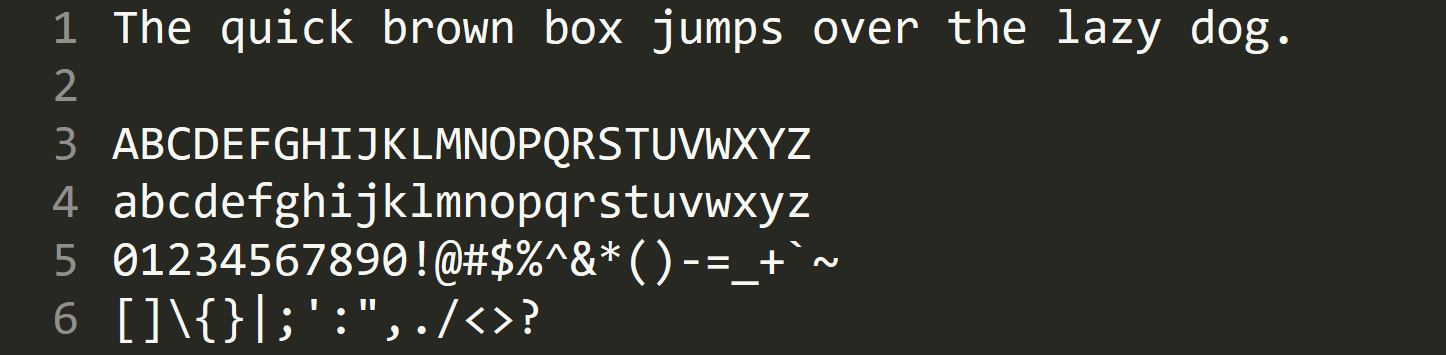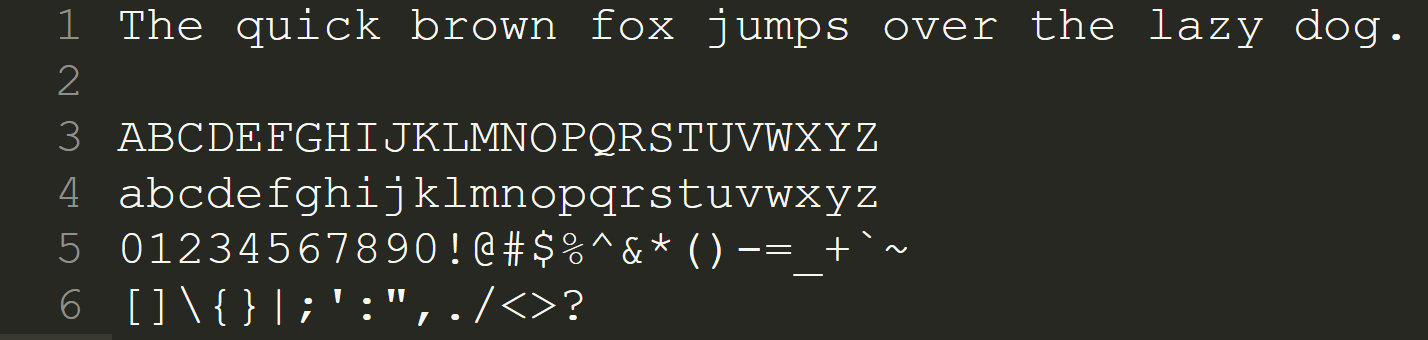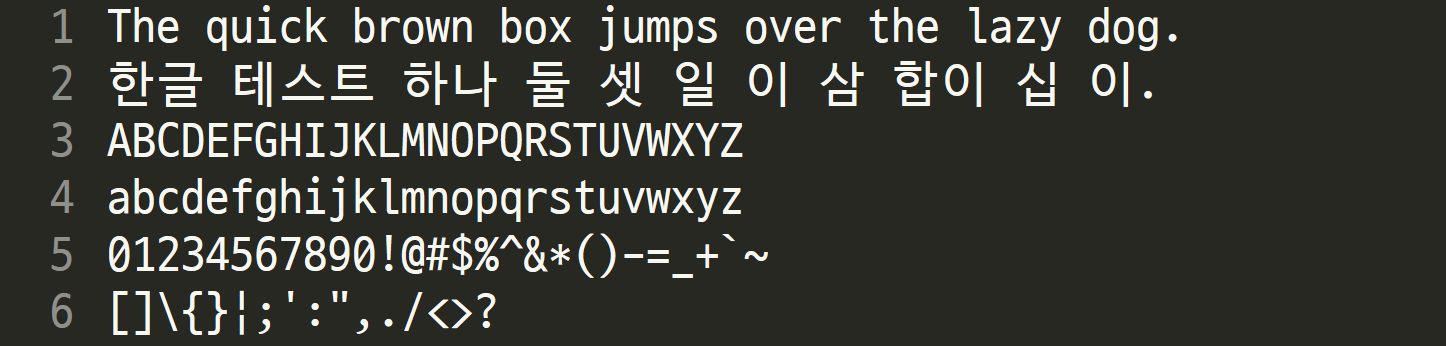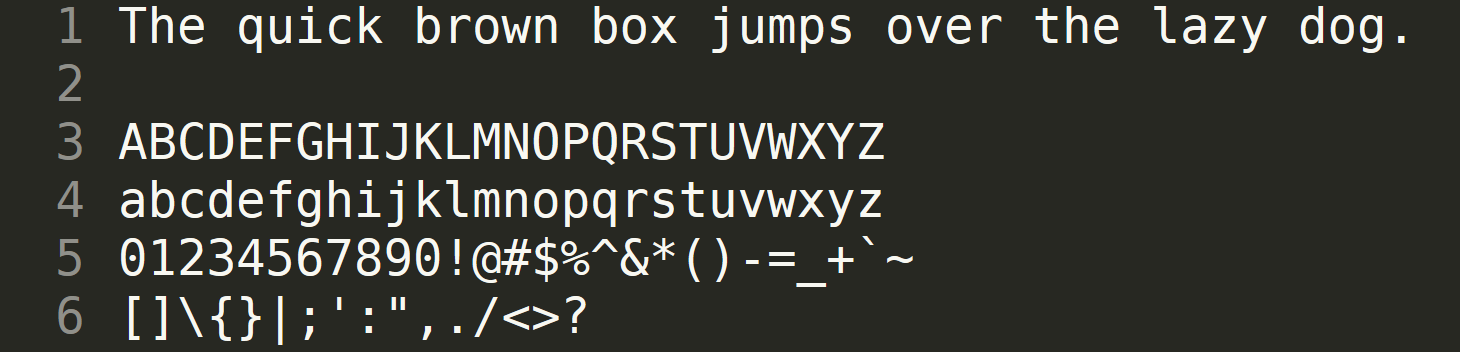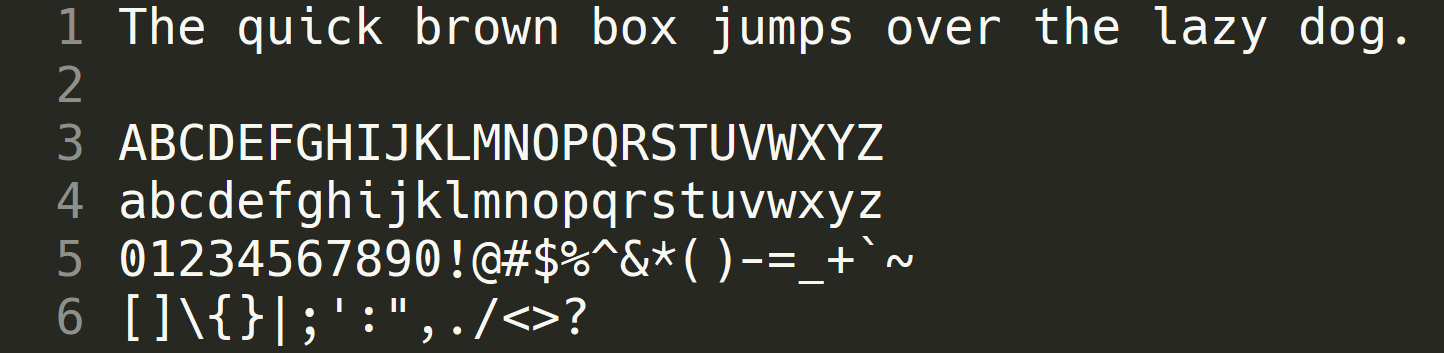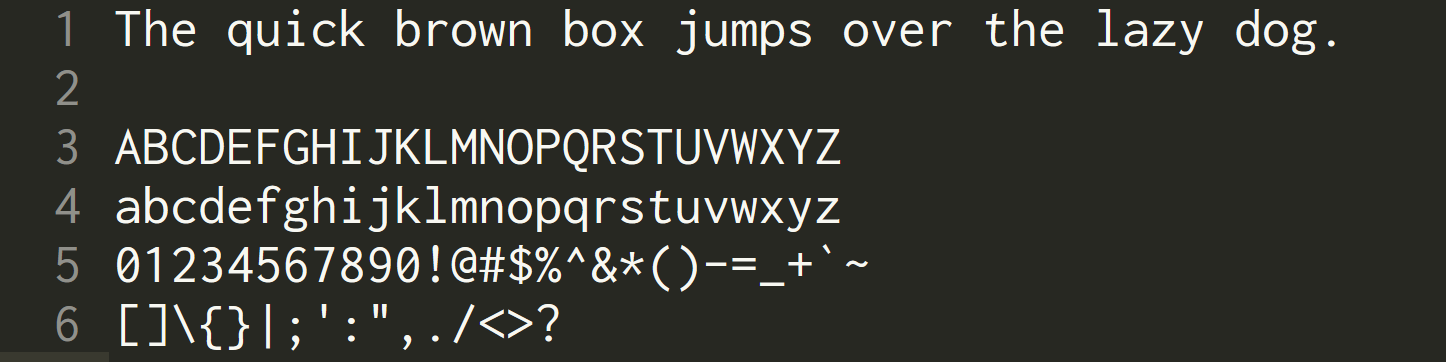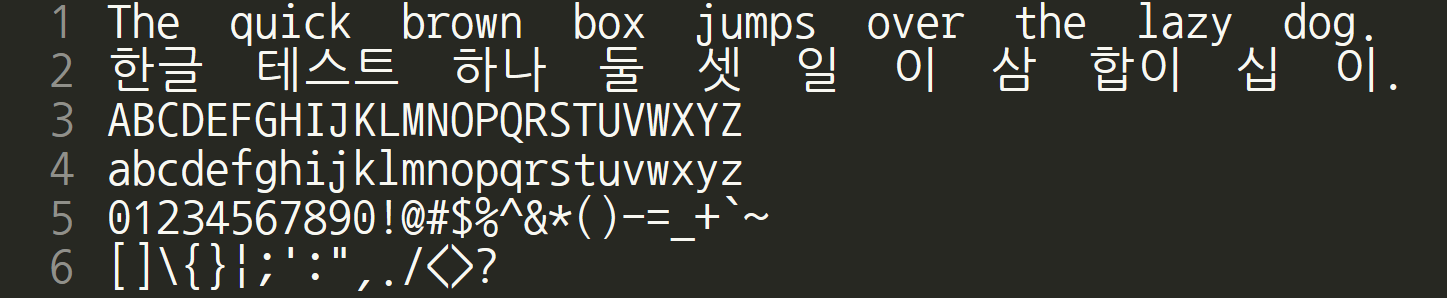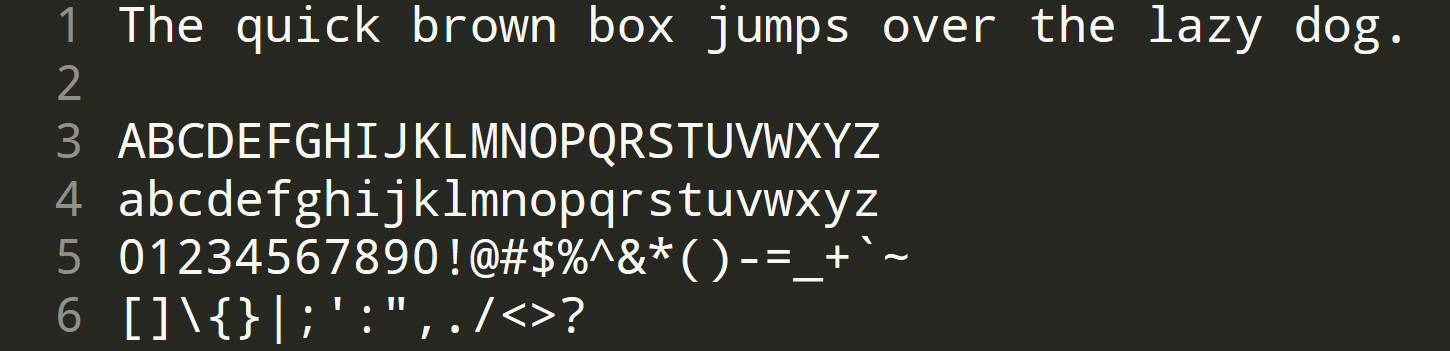
이공계 대학생/대학원생을 위한 컴퓨팅 강좌 8: 코딩용 고정폭 폰트(fixed-width font) 선택하기
고정폭 폰트의 필요성
코딩을 할 때는 기본적으로 글자의 가로 폭이 일정한 고정폭 폰트(fixed-width font)를 씁니다. 그 이유는 아무래도 터미널(terminal)에서 고정폭 폰트로 코딩을 하던 관습의 영향이 크겠습니다만 고정폭 폰트가 들여쓰기(indentation)와 같은 특성을 가진 소스 코드의 가독성을 높여준다는 이유도 있겠습니다.
그리고 코딩용 폰트는 1, i, l, | 이나 o, O, 0, @ 등과 같이 비슷하게 생긴 영문자, 숫자, 특수기호의 구분을 명확히 해야 하는 특성이 있습니다. 이것은 코딩을 할 때 한 글자만 틀려도 결과가 다르게 나오는 코딩의 특성 때문입니다. 실제 제 경우 학부시절에 for (j = i + 1; j < n; ++j)for (j = 1 + 1; j < n; ++j)로 잘못 적었다가 i와 1을 구분못해 디버깅에 일주일 가까이를 날려 버렸던 경험이 있습니다.
고정폭 폰트의 대표적 예: Courier
Courier New
윈도우 운영체제에서 기본으로 제공되는 코딩용 고정폭 폰트는 Courier 폰트가 있습니다. (Courier, Courier new) 타자기(typewriter)에 대표적으로 쓰이는 폰트입니다.
하지만 아쉽게도 Courier 폰트의 컴퓨터 화면 가독성은 그다지 좋지 않습니다. 그래서 코딩용으로는 Courier외에 다른 폰트들이 많이 쓰이는 편입니다.
고정폭 폰트 소개
그렇다면 Courier 이외의 가독성이 좋은 고정폭 폰트는 어떤 것이 있을까요? 여러가지 폰트 중에서 일단 무료, 혹은 상용이지만 쉽게 구할 수 있는 폰트를 우선적으로 알아보도록 하겠습니다.
Dejavu Sans Mono
리눅스 시스템에 거의 기본으로 들어가 있는 고정폭 폰트입니다. 원래는 Bitstream 회사에서 개발한 Vera 폰트를 기반으로 하고 있는데 라이센스가 Bitstream Vera 폰트보다 좀 더 자유롭다고 알려져 있습니다.
무료로 구할 수 있는 고정폭 폰트 중에서는 거의 최상의 가독성을 갖추고 있고, 유니코드까지 지원하는 장점이 있습니다.
Hack
Dejavu Sans Mono의 변종입니다. 폰트에 큰 차이는 없지만 0이나 , ; 같은 특수문자의 가독성을 높여서 좀 더 코딩에 특화된 폰트입니다. 제 경우 이 폰트를 코딩 주력으로 쓰고 있습니다.
Noto Mono
Android 운영체제를 위해 만들어진 Droid, Roboto 폰트 패밀리의 가장 최근 발전형입니다. 역시 무료로 사용 가능합니다. 참고로 Noto 폰트는 구글에서 진행하고 있는 Unicode 전체를 커버하는 폰트 프로젝트의 산물입니다. 안드로이드 스마트폰에서 볼 수 있는 한글 폰트가 Noto CJK (Chinese, Japanese, Korean) 폰트입니다.
Noto Mono 폰트는 전체적으로 Dejavu Sans Mono와 비슷하게 생겼습니다만 i, l 과 같은 글자들이 다르게 생겼습니다.
Inconsolata
Microsoft의 Office나 Visual Studio 패키지를 설치하면 추가되는 고정폭 폰트가 Consolas 폰트입니다. 그런데 Consolas 폰트는 상용이라 배포가 자유롭지 못한 불편이 있습니다. Inconsolata 폰트는 이름에서 엿볼 수 있듯이 Consolas 폰트의 영향을 받은 무료 폰트로 처음부터 해상도가 높은 화면에서 더 깨끗하게 출력되는 고품질의 코딩용 폰트 개발을 지향했다는 특성이 있습니다.
Consolas
Incosolata에서 말씀드렸듯이 Microsoft의 Office나 Visual Studio 패키지를 설치하면 추가되는 가독성이 좋은 고정폭 폰트입니다.
Cousine font
Cousine
Chrome OS의 Core 폰트 시리즈에 포함되어 배포되는 고정폭 폰트입니다. Courier new와의 자간 metric 호환에 신경을 썼다고 합니다. Chromebook을 쓰면 디폴트로 볼 수 있는 폰트가 되겠습니다.
한글 고정폭 폰트
D2Coding 폰트
D2Coding
나눔 코딩
Nanum Gothic Coding
D2Coding 폰트가 나오기 전에 많이 쓰였던 한글 고정폭 폰트입니다. 나눔 고딕 코딩도 좋은 폰트이지만 전체적으로 서체가 너무 가늘고 고해상도 화면에서는 D2Coding이 더 나은 출력 품질을 보여 줍니다.
고정폭 폰트 소개를 마치면서
지금까지 코딩에 적합한 가독성 좋은 고정폭 폰트에 대해 알아보았습니다. 개인적으로 볼 때 전체적으로 Dejavu Sans Mono 계열 폰트들이 가독성이 좋고 무난한 느낌이며 한글 고정폭 폰트로는 D2Coding 폰트가 상당히 뛰어나다고 생각합니다.
폰트 선택은 주관적인 취향이 작용하기 때문에 위에 열거한 폰트 이외에 다른 선택을 하셔도 좋겠습니다. 다만, 코딩을 할 때에는 고정폭 폰트가 아닌 일반 가변폭 폰트 (variable-width font)를 쓰지는 마시기를 부탁드립니다.